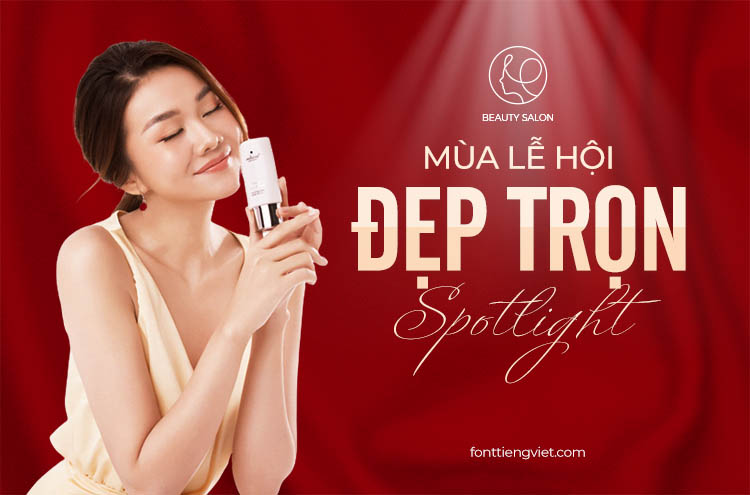
Font combo thiết kế mỹ phẩm 1 – Sẳn hiệu ứng trong file Ps
Font combo thiết kế mỹ phẩm 1 – Sẳn hiệu ứng trong file Ps và bộ bí quyết sáng tạo bao bì chuyên nghiệp
Giới thiệu về Font combo thiết kế mỹ phẩm 1 – Sẳn hiệu ứng trong file Ps
Trong ngành công nghiệp làm đẹp, việc sở hữu một diện diện mạo thương hiệu ấn tượng là yếu tố then chốt để thu hút khách hàng ngay từ cái nhìn đầu tiên. Hiểu được nhu cầu đó, bộ Font combo thiết kế mỹ phẩm 1 – Sẳn hiệu ứng trong file Ps đã ra đời như một giải pháp toàn diện cho các nhà thiết kế đồ họa. Đây không chỉ đơn thuần là các kiểu chữ thông thường mà còn là một hệ sinh thái sáng tạo, nơi các Font Miễn Phí được tinh chỉnh và đóng gói sẵn kèm theo các hiệu ứng đổ bóng, ánh sáng và chất liệu đặc thù của ngành mỹ phẩm. Việc sử dụng bộ combo này giúp người dùng tiết kiệm tối đa thời gian dàn trang và xử lý kỹ thuật phức tạp trên phần mềm Adobe Photoshop.
Tại sao nên chọn Font combo thiết kế mỹ phẩm 1?
Điểm khác biệt lớn nhất của Font combo thiết kế mỹ phẩm 1 – Sẳn hiệu ứng trong file Ps nằm ở tính tiện dụng vượt trội. Thông thường, để tạo ra một dòng chữ có độ bóng gương hoặc hiệu ứng nhũ vàng sang trọng, bạn phải mất hàng giờ đồng hồ để tinh chỉnh layer style. Tuy nhiên, với tệp tin này, mọi thứ đã được thiết lập sẵn trong các Smart Object. Bạn chỉ cần thay đổi nội dung văn bản và toàn bộ hiệu ứng thị giác đỉnh cao sẽ tự động áp dụng, mang lại vẻ ngoài cao cấp cho sản phẩm serum, son môi hay kem dưỡng da của mình.
Chi tiết các thành phần trong bộ Font combo thiết kế mỹ phẩm 1 – Sẳn hiệu ứng trong file Ps
Bộ sưu tập này tập trung vào sự thanh lịch, tinh tế và hiện đại, phản ánh đúng tinh thần của các dòng mỹ phẩm thiên nhiên hoặc dược mỹ phẩm cao cấp. Các kiểu chữ trong combo được tuyển chọn kỹ lưỡng để đảm bảo khả năng hiển thị tốt trên cả bao bì in ấn lẫn hình ảnh quảng cáo trực tuyến.
Sự đa dạng về phong cách chữ
Bên trong Font combo thiết kế mỹ phẩm 1 – Sẳn hiệu ứng trong file Ps, bạn sẽ tìm thấy sự kết hợp hoàn hảo giữa các phông chữ Serif (có chân) mang tính cổ điển, quý phái và các phông chữ Sans-serif (không chân) hiện đại, tối giản. Sự tương phản này tạo nên một bố cục hài hòa, giúp phân tách rõ ràng giữa tên thương hiệu, tên sản phẩm và các thông số kỹ thuật. Đặc biệt, tất cả các font chữ đều đã được việt hóa hoàn chỉnh, giúp các designer Việt Nam không còn lo lắng về lỗi font khi gõ tiếng Việt có dấu.
Hiệu ứng độc quyền trong file Photoshop
Không chỉ dừng lại ở mặt chữ, tệp tin đi kèm còn chứa các lớp Layer Style độc đáo như hiệu ứng dập nổi (emboss), hiệu ứng mạ vàng (gold foil), và hiệu ứng chữ neon mềm mại. Những công cụ này được thiết kế chuyên biệt để tương thích với các bảng màu trung tính như màu be, trắng sứ hoặc xanh lá mướt, tạo nên một tổng thể thiết kế mỹ phẩm chuẩn quốc tế.
Hướng dẫn sử dụng và tối ưu hóa thiết kế
Để tận dụng tối đa sức mạnh của Font combo thiết kế mỹ phẩm 1 – Sẳn hiệu ứng trong file Ps, người dùng nên lưu ý về phân cấp thị giác. Hãy sử dụng các font chữ bay bổng cho phần slogan và giữ sự nghiêm túc, dễ đọc cho phần thành phần sản phẩm. Việc cài đặt cũng rất đơn giản, bạn chỉ cần giải nén tệp tin, cài đặt font vào hệ thống và mở file .PSD đi kèm để bắt đầu sáng tạo. Đây thực sự là công cụ không thể thiếu cho những ai muốn nâng tầm thương hiệu cá nhân hoặc doanh nghiệp trong lĩnh vực làm đẹp.